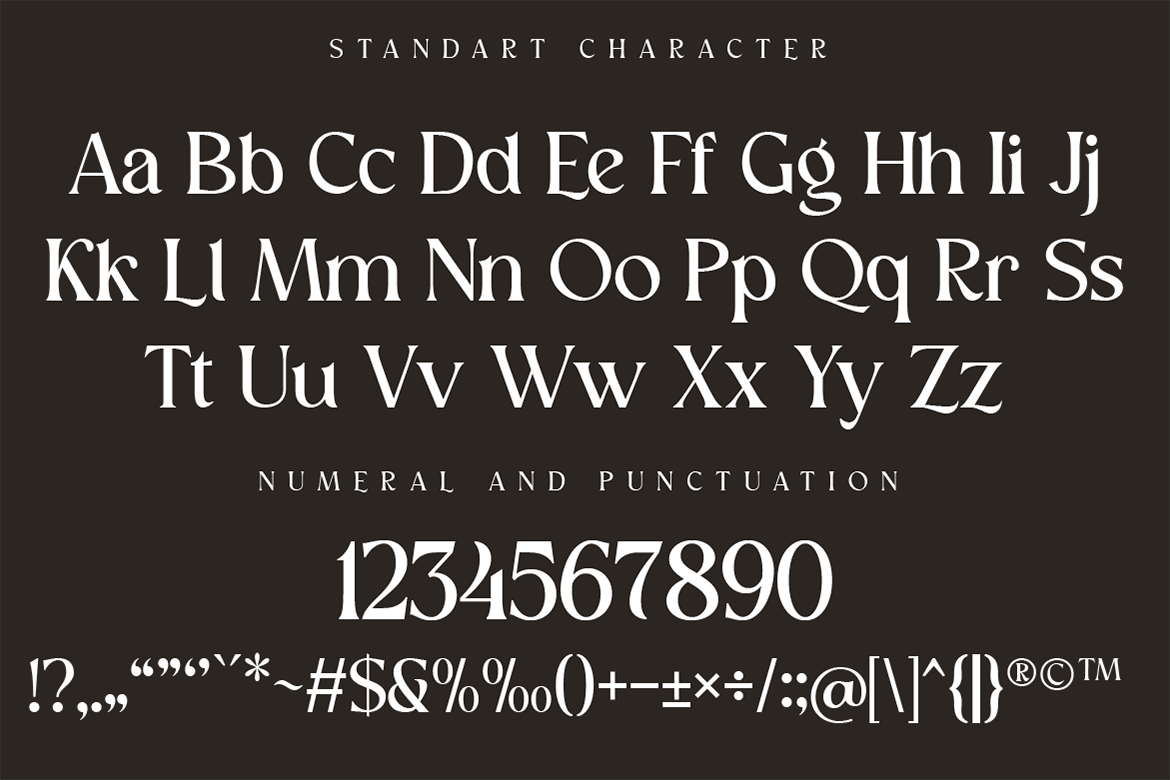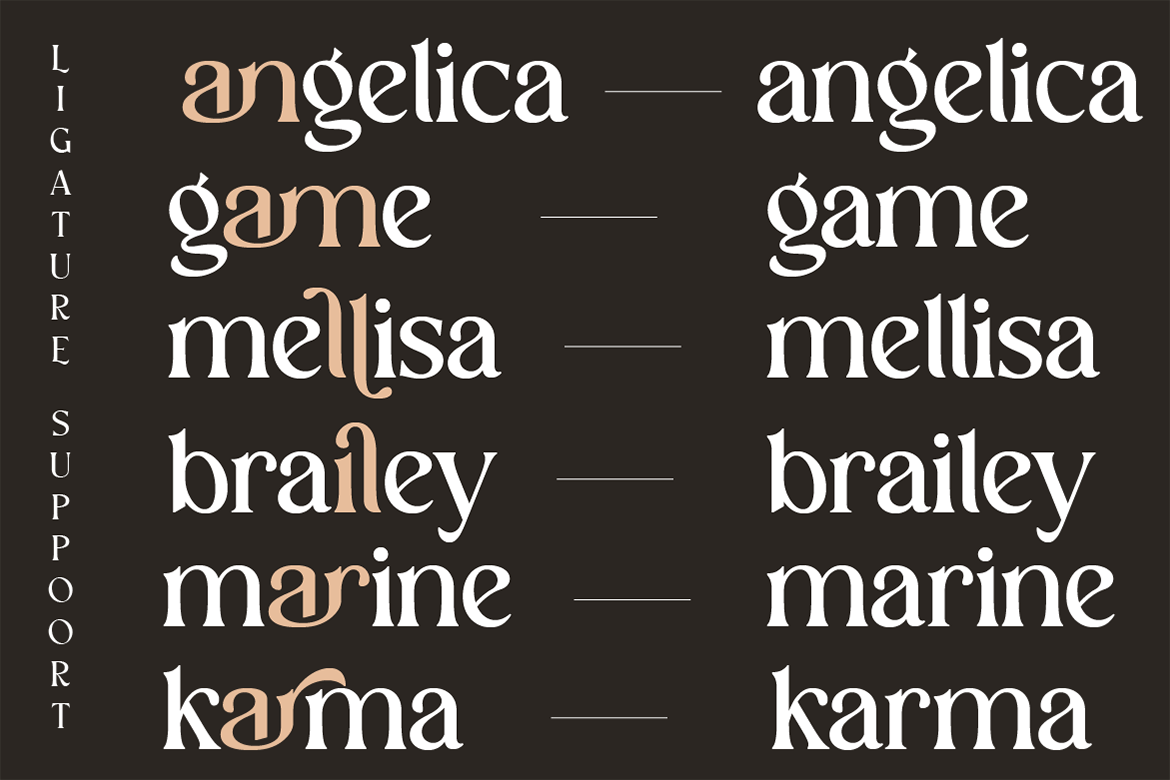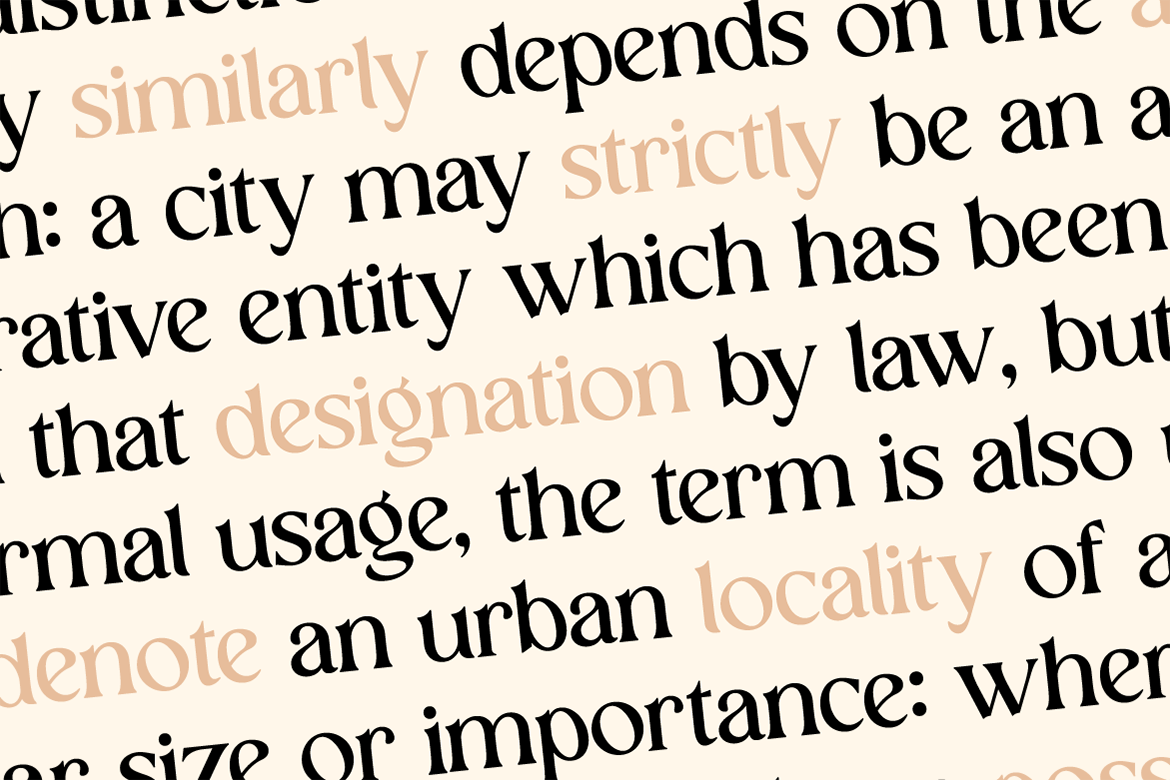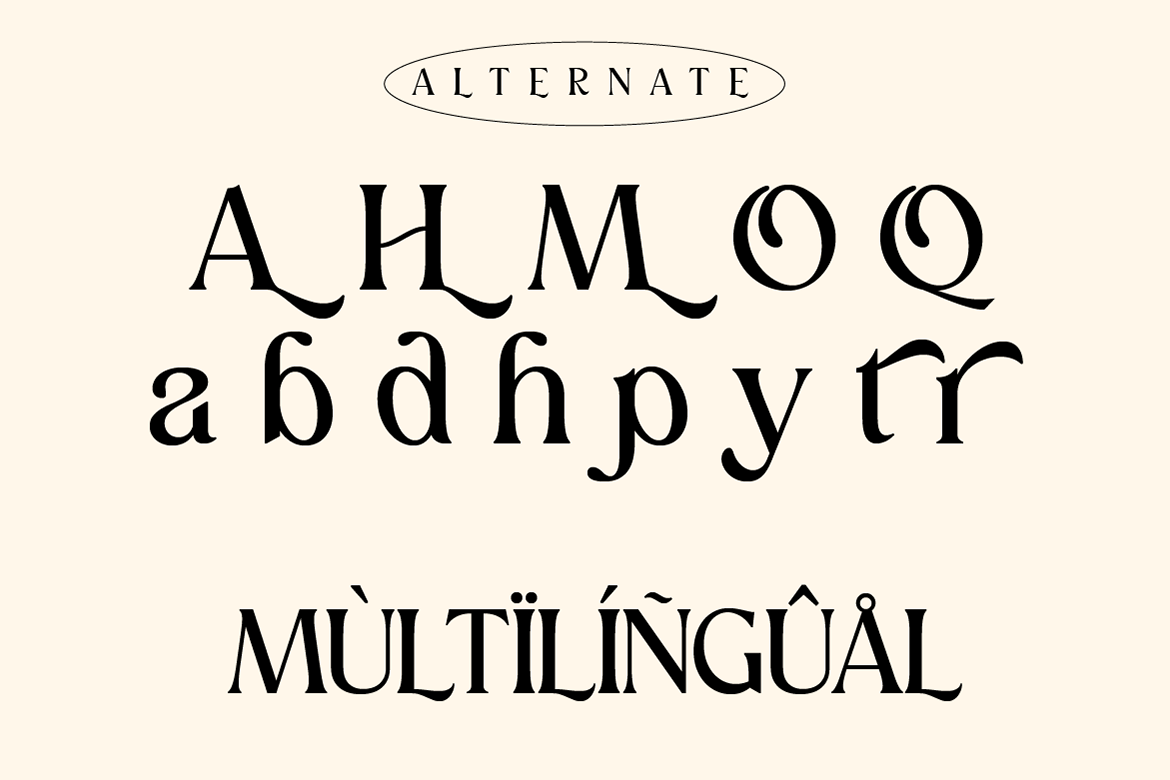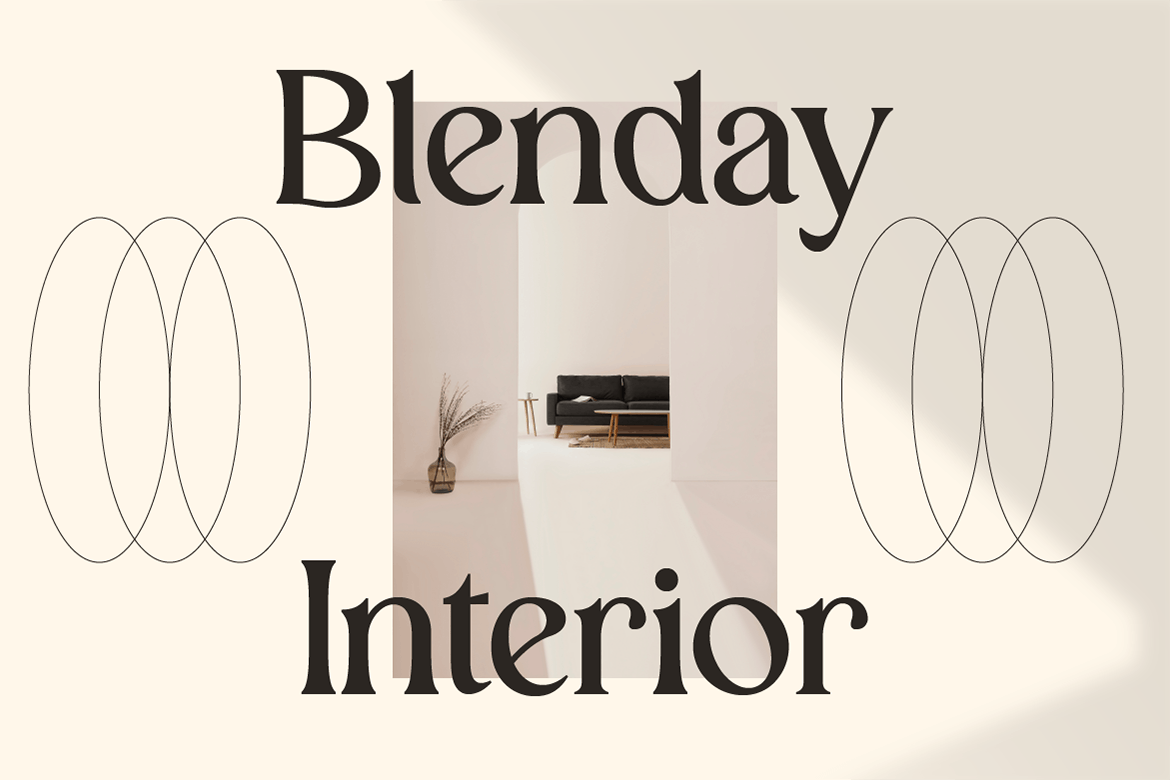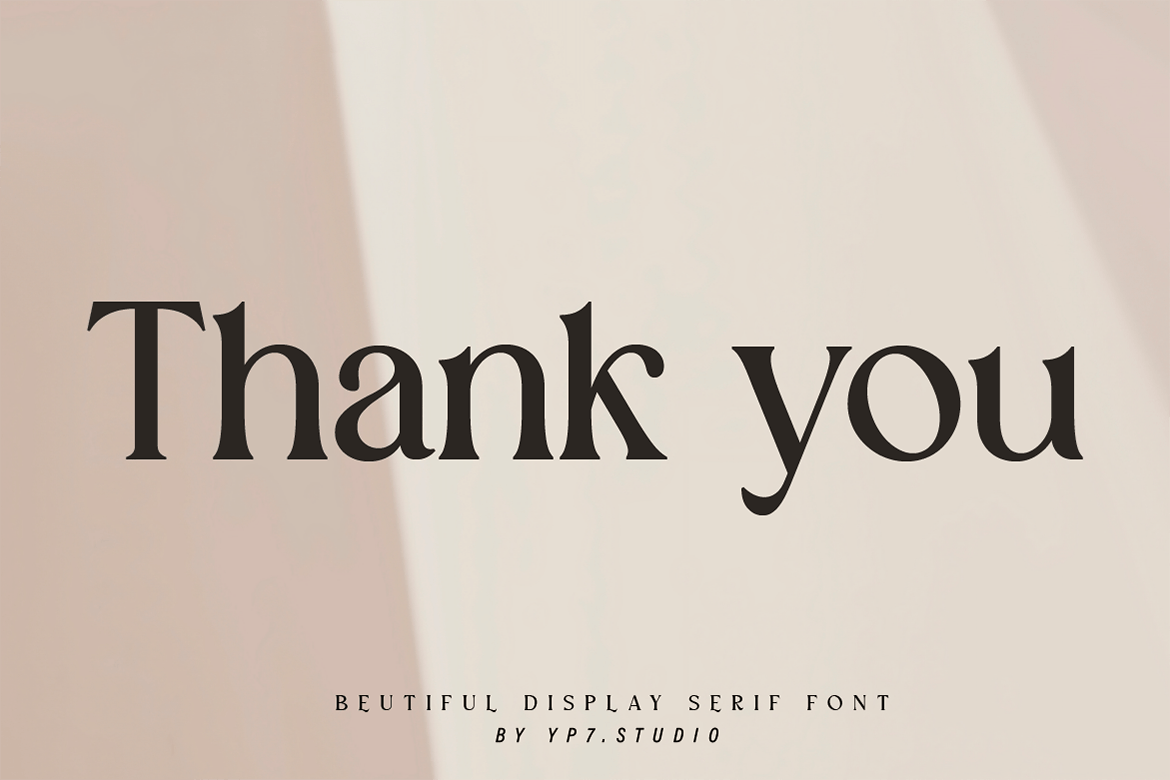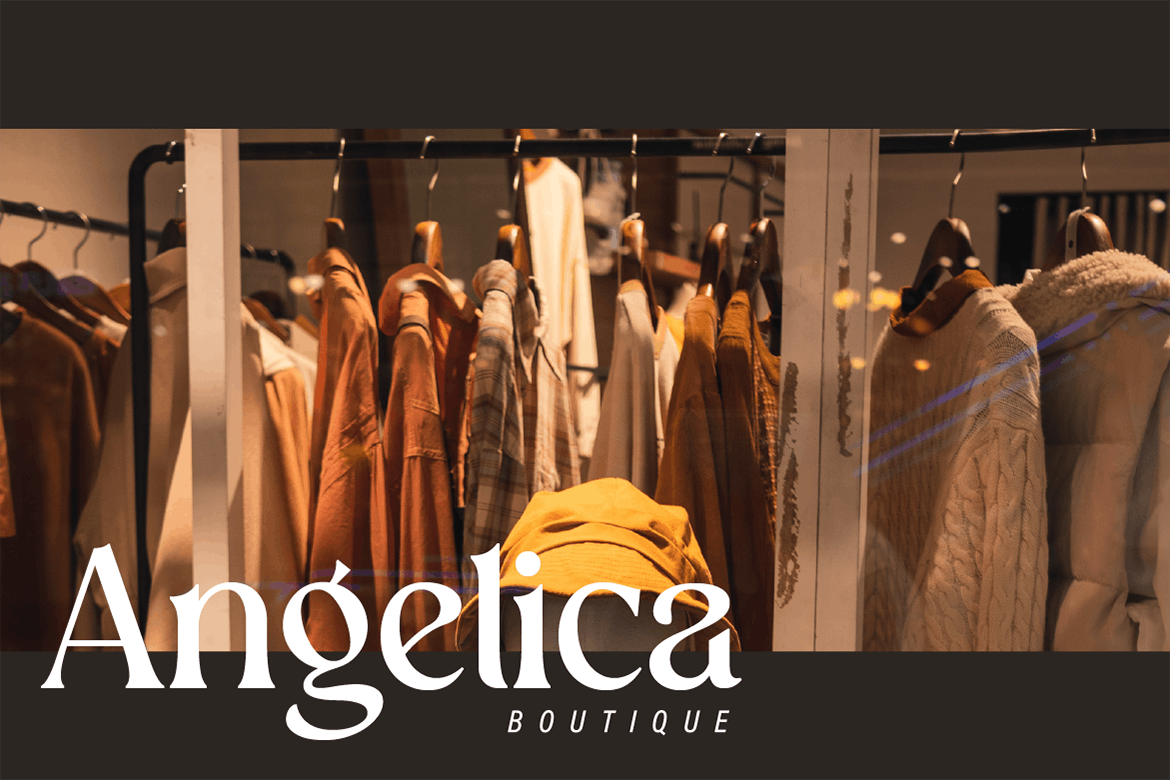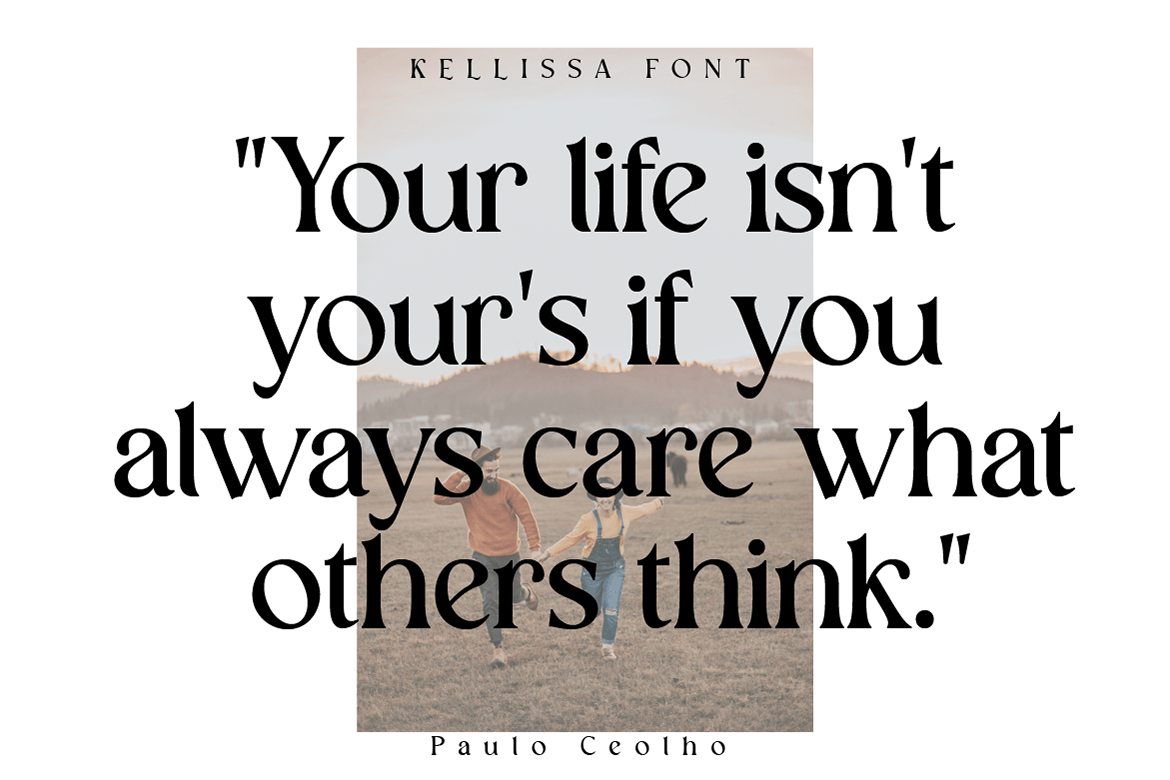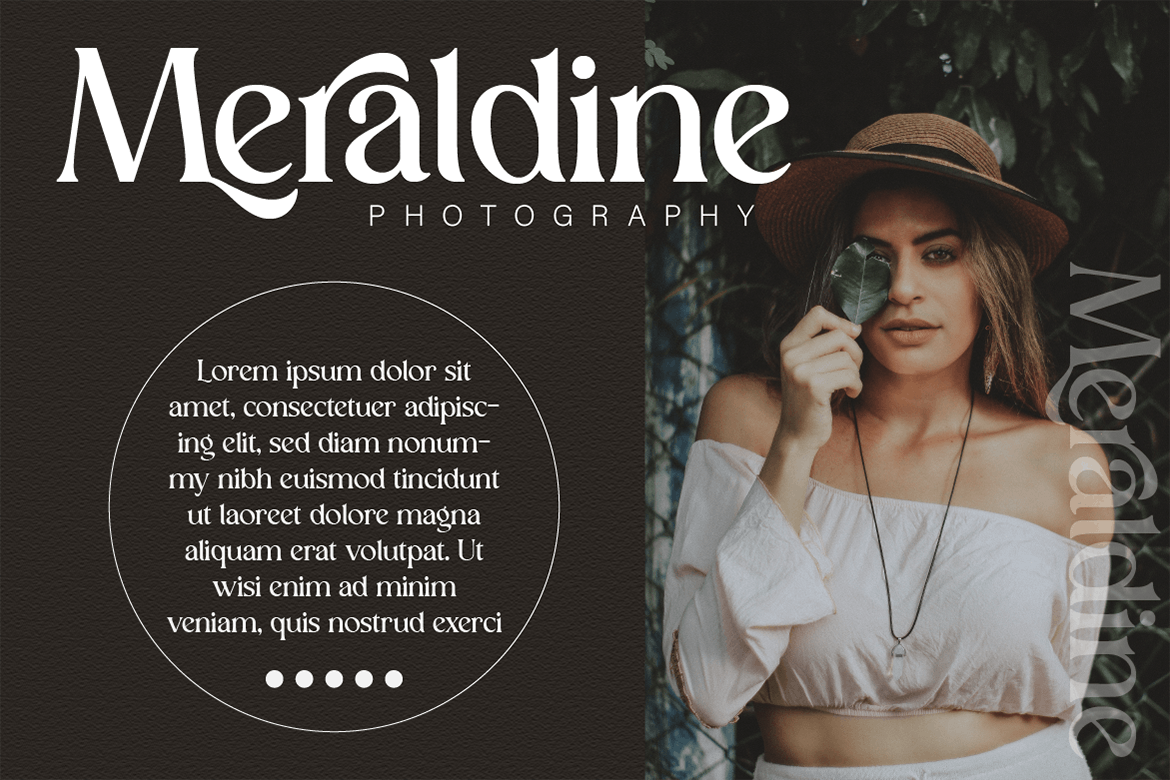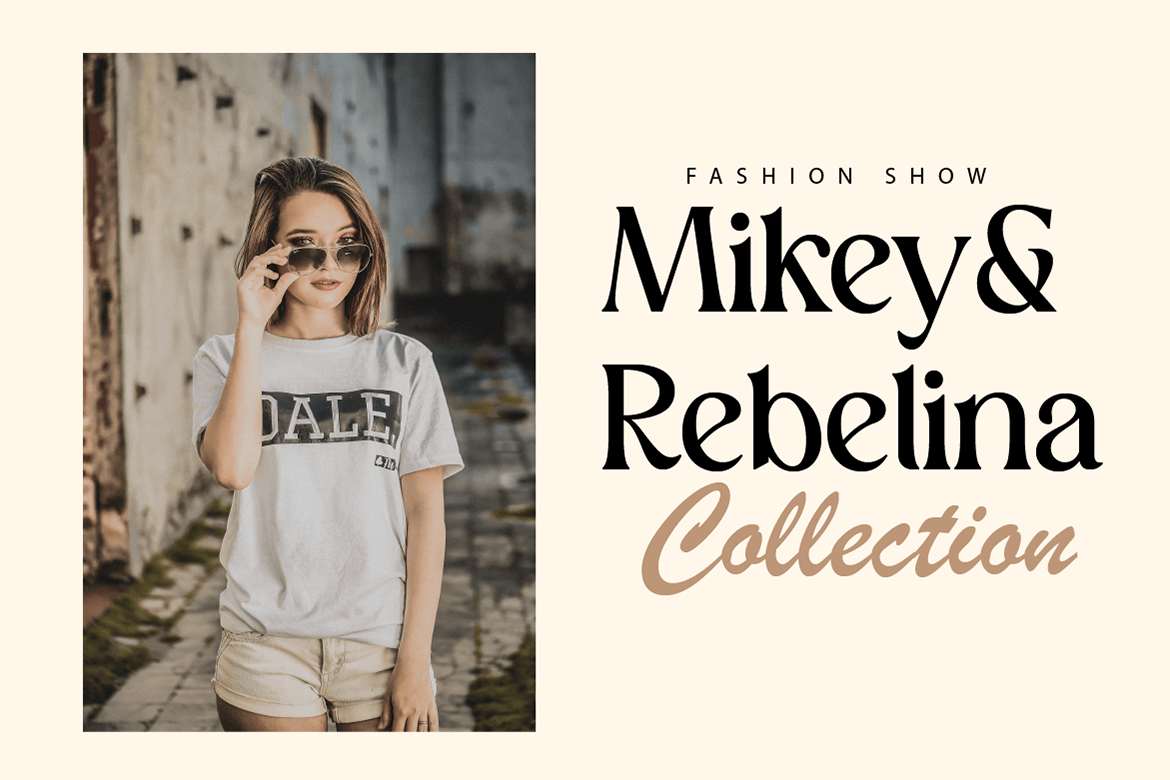
Modern Luxury Display Font
فونت Kellisa با طراحی لوکس و مدرن، انتخابی ایده‌آل برای پروژه‌های شماست.
Kellisa Modern Luxury Display Font یک فونت نمایش لوکس و مدرن است که به زیبایی طراحی شده و مناسب برای انواع پروژه‌های گرافیکی می‌باشد.
• حروف بزرگ
• حروف کوچک
• اعداد و نشانه‌گذاری